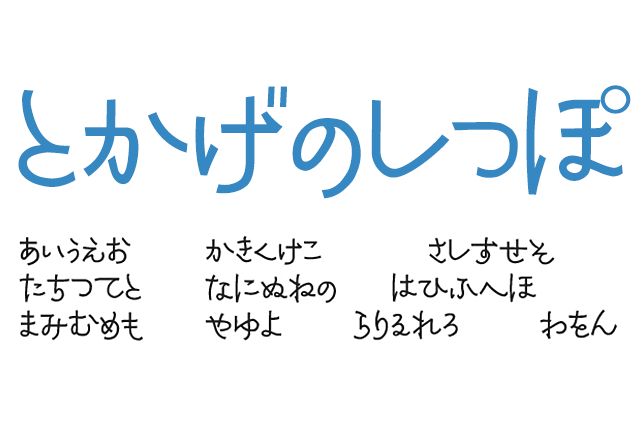
Tokage-no-Shippo HR 2021.12.07 2016.09.12Tokage-no-Shippo HRは、癖の強い手書き風のゴシック体の1byteひらがなフォントです。アラビア文字のような独特のウネリが特徴的です。ライセンス無料で使える商用可のフリーフォントです。ダウンロードTokage-no-Shippo HRフォント情報ライセンス商用可カテゴリー日本語 > 手書き風タグ手書き風作者・シリーズフォント910※当サイトはフォントの紹介サイトです。フォントを利用の際には必ず「フォントの利用について」をご覧ください。